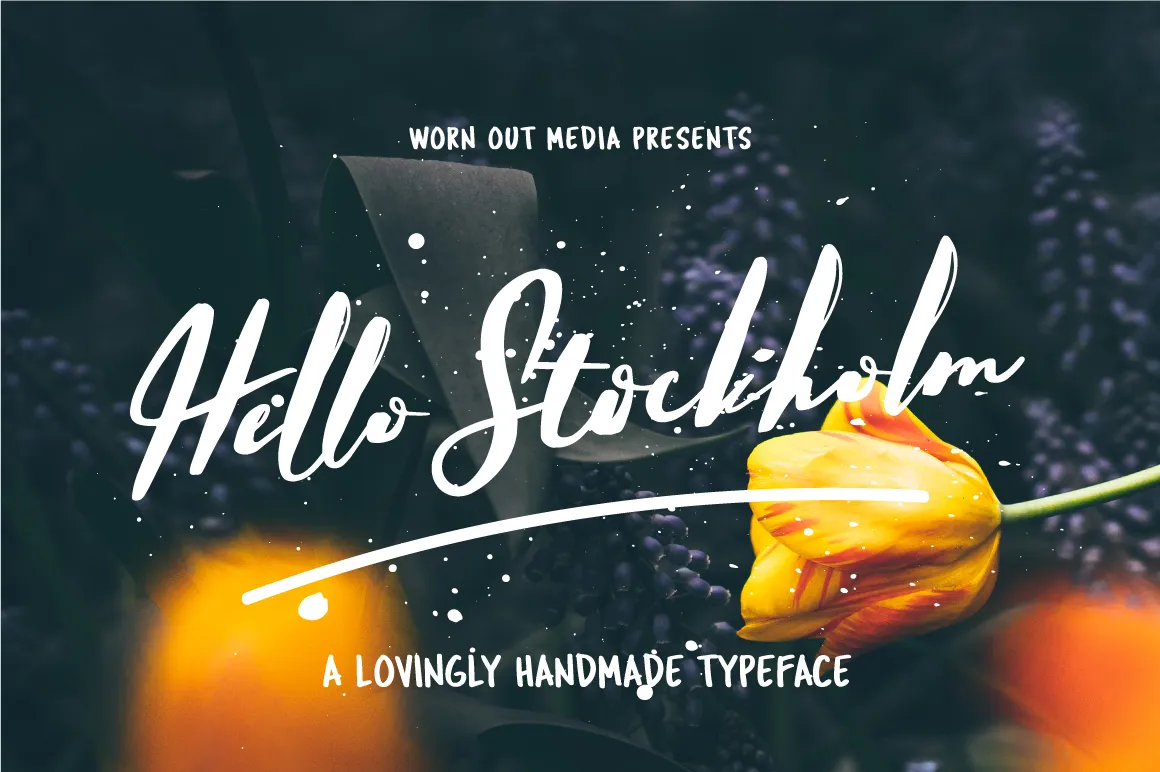
Hello Stockholm - Handmade Typeface
Introduzimos uma nova tipografia feita à mão, Hello Stockholm! Esta é uma fonte com traços modernos e um estilo script, cheia de característica e originalidade, inspirada na simplicidade escandinava. Obrigado ao designer 178-MC pela elaboração desta fonte chamativa que transmite um toque único de criatividade. Ideal para criar texturas interessantes em design gráfico, esta fonte se encaixa perfeitamente no estilo Brush Fonts. Com um toque leve de minimalismo escandinavo, Hello Stockholm oferece uma combinação ideal de elegância e excentricidade que certamente cativará designers em busca de algo novo e inspirador.